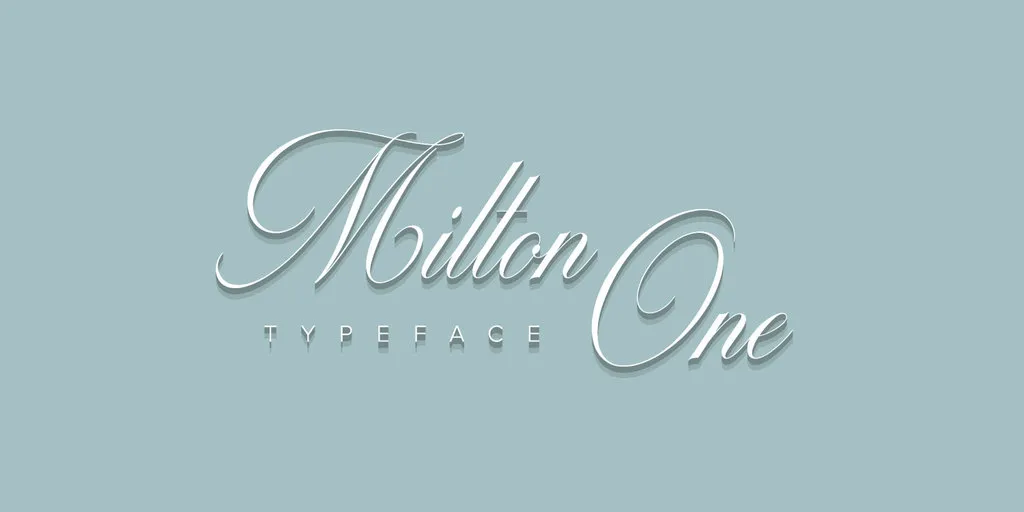
Milton One Font Family – Download Grátis
A fonte Milton One Font Family é uma família completa de fontes compostas por linhas manuscritas e é perfeita para quem busca uma aparência única e elegante para projetos pessoais ou comerciais, mas com um toque diferente que não se sobrepõe a outras. Suas linhas são levemente suaves e fluidas, oferecendo um apelo natural que cria um contato próximo com os leitores. Especialmente interessante é o fato de esta fonte ser perfeita para uso pessoal sem custos adicionais, mas para qualquer aplicação comercial, há a opção de entrar em contato diretamente com o designer, Hamilton. Este atendimento personalizado garante que você possa explorar as infinitas maneiras de expressar seu design na arena do mercado. Independentemente do tipo de projeto que você está trabalhando, Milton One Font Family certamente se encaixa perfeitamente, e é claro que a qualidade da fonte não poderia ser melhor para quem busca um toque autêntico em seus projetos digitais. Esta fonte foi desenvolvida pelo designer Hamilton, conhecido por suas habilidades únicas de criar designs originais e personalizados. Se você estiver procurando por uma font que transmite sua personalidade ou cria um impacto único nas páginas dos seus projetos, Milton One Font Family é certamente o tipo de recurso gráfico inestimável que você precisa no seu arsenal.